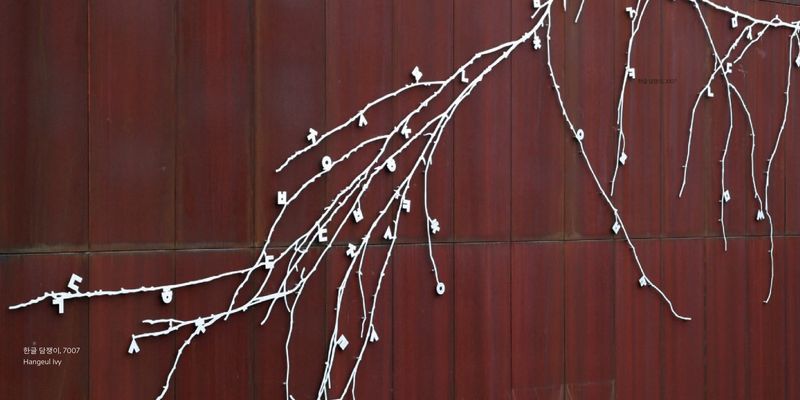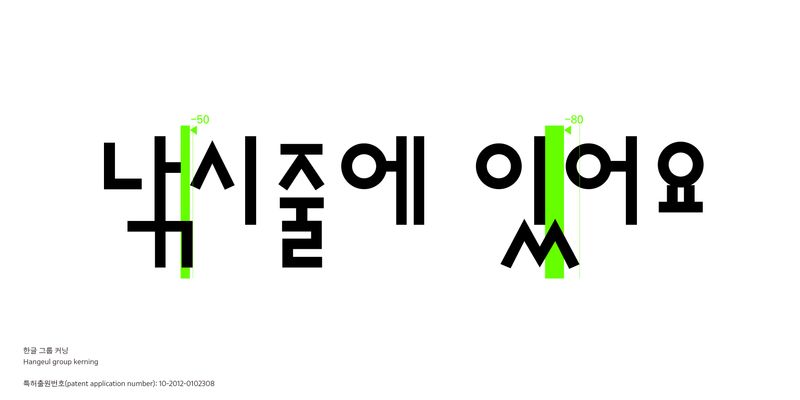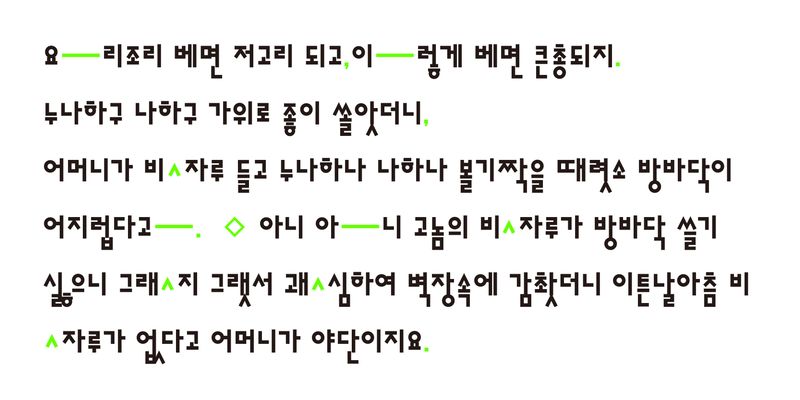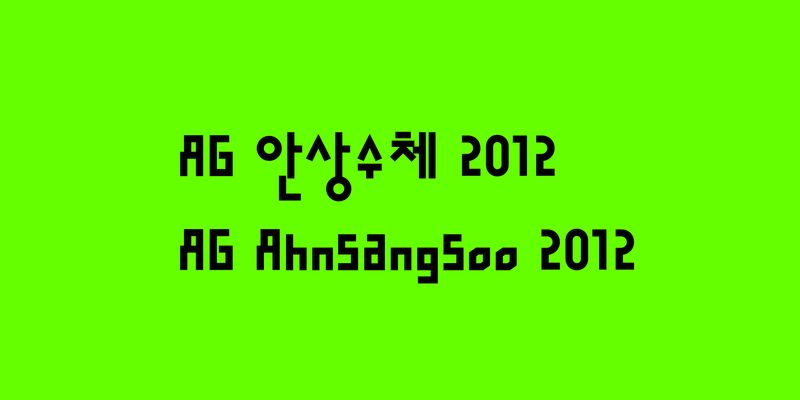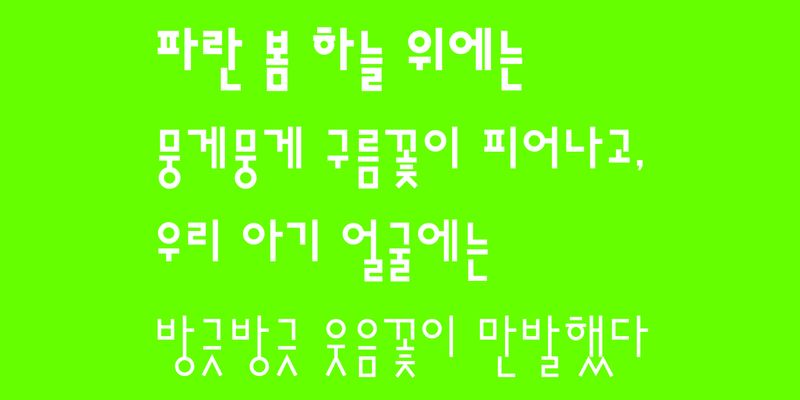
El tipo de letra Ahnsangsoo consta de tres conjuntos de letras redondeadas diseñados por Ahn Sang-Soo en 1985.
Consta de 19 consonantes, 21 vocales, 27 consonantes finales, que se combinan para derivar
11.172 letras hangul. Cada carácter se compone de formas geométricas, como líneas horizontales, verticales, diagonales y círculos perfectos. Los largos trazos de las vocales se han extendidos para llegar al centro de las consonantes finales.
AG Ahnsangsoo 2012 es una versión mejorada de la tipografía Ahnsangsoo, basada en las investigaciones del Instituto de Tipografía AG. Las letras hangul, los alfabetos latinos y los números se han ajustado visualmente para mejorar la legibilidad. Este tipo de letra redondeado de varios conjuntos es el primero en aplicar el “interletraje de grupo hangul”.